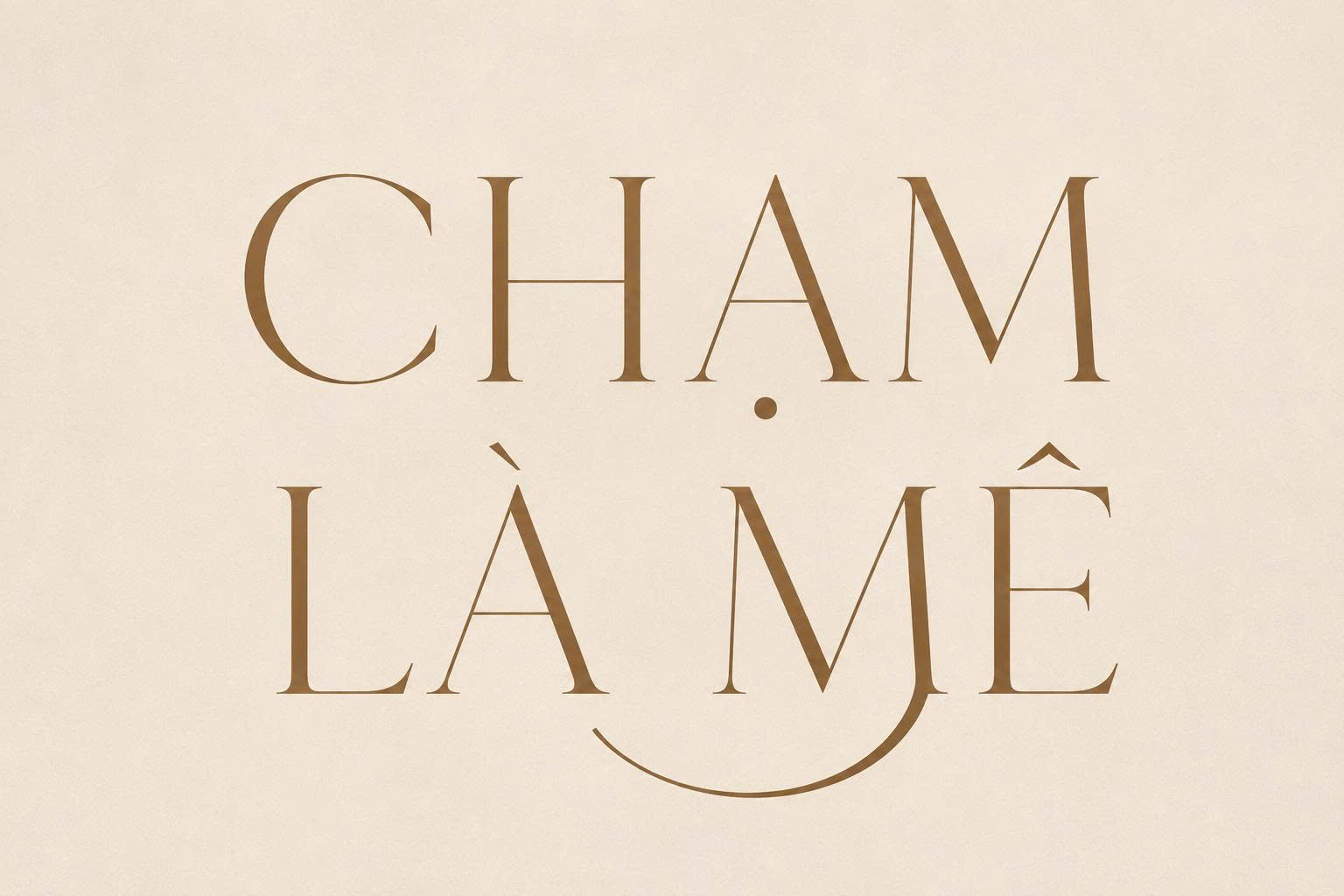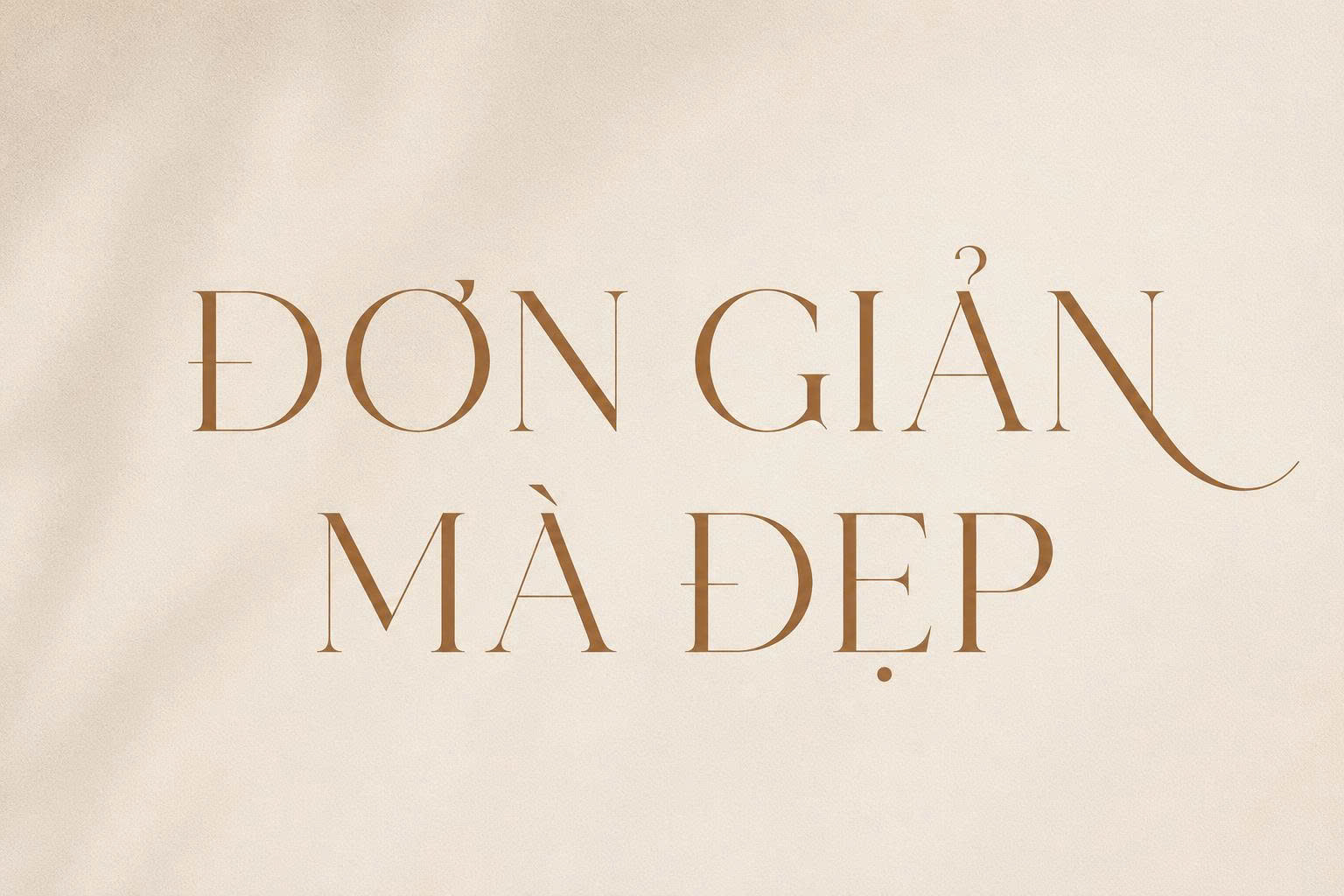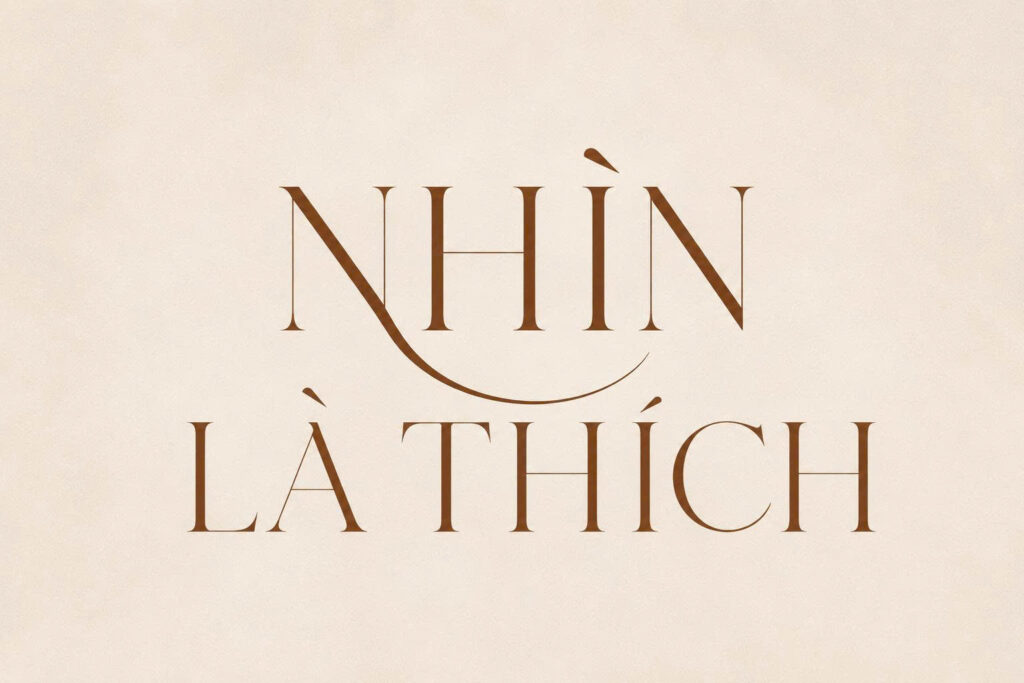
Font Việt hóa Menata là bộ phông chữ thuộc dòng Luxury Display Serif do Alit Design sáng tạo, nổi tiếng với sự kết hợp hài hòa giữa nét chân chữ thanh mảnh, các đường cong uốn lượn thời thượng và hệ thống ký tự nối nét đầy vẻ quyến rũ. Mang diện mạo đài các, hiện đại và phảng phất phong cách sống thượng lưu, font Việt hóa Menata là chất liệu trực quan tuyệt vời để các kiến trúc sư, nhà thiết kế nâng tầm không gian cho các bản vẽ phối cảnh spa chăm sóc sắc đẹp container, homestay nghỉ dưỡng cao cấp hay bộ nhận diện thương hiệu nội thất sang trọng.
Đường nét kiêu kỳ và nghệ thuật liên kết chữ của font Việt hóa Menata
Điểm cuốn hút của font Việt hóa Menata nằm ở tỷ lệ tương phản sắc sảo giữa các thân chữ thẳng đứng và các nét ngang thanh mảnh như sợi chỉ, kết hợp cùng các đường vòng cung mềm mại ở các ký tự liên kết. Khác với các dòng Serif truyền thống có phần nặng nề, Menata mang lại cảm giác nhẹ nhõm, bay bổng và đượm chất thời trang Paris đương đại.
Sự ổn định về mặt thị giác của dòng font này giúp khẳng định gu thẩm mỹ tinh tế, sự chu đáo và phong cách sống hưởng thụ của đơn vị chủ trì dự án. Khi xuất hiện trên các bề mặt vật liệu kiến trúc hiện đại như đá cẩm thạch trắng, kim loại inox mạ vàng xước mờ, vách kính cường lực trong suốt hay rèm lụa trong các căn nhà lắp ghép nghỉ dưỡng, Menata tạo nên điểm nhấn thị giác cuốn hút.
| Phân loại phong cách | Luxury Display Serif / Ligature / Fashion Editorial |
| Mục đích phù hợp | Biển tên spa, bìa hồ sơ năng lực, logo thời trang |
Tư vấn từ chuyên viên: Menata sở hữu các nét thanh mảnh và độ tương phản lớn. Để bản thiết kế đạt hiệu quả thẩm mỹ tốt, bạn nên sử dụng phông chữ này cho các tiêu đề chính, tên công trình hoặc câu khẩu hiệu ngắn ở kích thước lớn từ 18pt trở lên.
03 Ứng dụng font Việt hóa Menata vào công trình thực tế
Nhờ vẻ ngoài quý phái và tính nghệ thuật phong phú, bộ phông chữ này mang lại giá trị thực tế lớn trong khâu tạo điểm nhấn cho các công trình hiện đại:
- Biển hiệu mặt tiền cho Spa Làm đẹp và Tiệm Nail Container: Những nét chữ thanh lịch của font Việt hóa Menata rất ăn ý khi gia công chữ nổi bằng inox vàng gương lồng đèn LED hắt chân, mang lại diện mạo đài các và thu hút khách hàng nữ ghé thăm trải nghiệm dịch vụ.
- Bìa hồ sơ năng lực dự án kiến trúc nghỉ dưỡng: Sử dụng font này cho tên dự án và tiêu đề các chương mục giúp hồ sơ trông như một ấn phẩm tạp chí kiến trúc danh giá, thể hiện gu thẩm mỹ sắc sảo của đơn vị kiến tạo.
- Hệ thống biển tên phòng và Bảng chỉ dẫn Khu nghỉ dưỡng cao cấp: Phông chữ này khi in trên kính mờ hoặc kim loại phủ sơn tĩnh điện sẽ giúp không gian sảnh đón tiếp và hành lang toát lên chất nghệ thuật thanh lịch.
03 Lưu ý bố cục font Việt hóa Menata Regular luôn thanh nhã và bắt mắt
Để khai thác hiệu quả vẻ đẹp của dòng font thời trang quý tộc này mà không làm ảnh hưởng đến khả năng đọc của bản vẽ, người thiết kế nên lưu tâm một số kinh nghiệm sau:
- Kích hoạt tính năng OpenType Ligatures: Trong các phần mềm thiết kế chuyên nghiệp như Illustrator hay Photoshop, bạn hãy bật bảng OpenType để tận dụng các nét nối chữ tự động của font Việt hóa Menata Regular, giúp câu chữ đạt được độ mềm mại và tinh tế đúng ý đồ của tác giả.
- Tránh sử dụng ở kích thước quá nhỏ: Do có các nét thanh mỏng manh, Menata hiển thị đẹp nhất ở kích thước chữ từ trung bình trở lên trong in ấn. Ở kích thước quá nhỏ, nét thanh có thể bị mờ nhòe do độ phân giải máy in hoặc thớ giấy.
- Bố trí nền màu đơn sắc tương phản: Menata phát huy hiệu quả thị giác cao khi đặt trên các nền màu đơn sắc có chiều sâu như đen tuyền, trắng ngọc trai, xám than hoặc xanh rêu sẫm, giúp các đường nét sắc sảo của bộ chữ được tôn vinh rõ ràng.
2. Phông chữ này có hỗ trợ các mối nối chữ cái (Ligatures) tự động không?